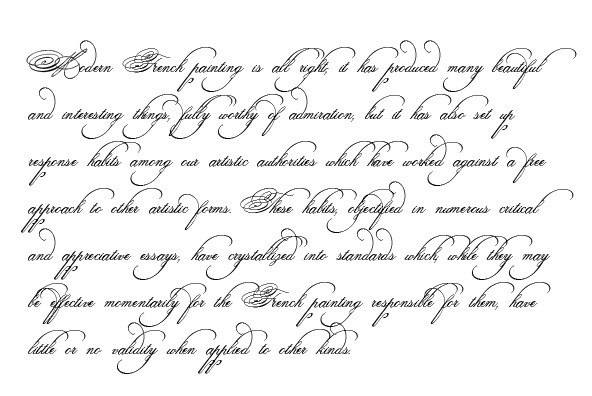
Каллиграфический почерк — как научиться писать красиво
В блогах, посвященных каллиграфии, уделяется много внимания способам создания красивых форм букв с помощью пера и чернил, но не так просто найти информацию по повседневному письму! В этом посте я раскрою восемь хитростей создания красивых рукописных записей любой ручкой на ваш вкус. А еще вы можете скачать прописи, чтобы отточить свой почерк!
Многие считают, что каллиграфия и есть красивый почерк, но это не так. Вообще, в каллиграфии буквы стилизованы и украшены – она ближе к искусству, нежели к простому письму. Письмо же, напротив, – совокупность знакомых приемов и стиль ежедневных заметок. В отличие от каллиграфии, в повседневном письме важнее скорость и удобство. А раз у каждого уникальный почерк, значит, возможности его совершенствования безграничны! Вот восемь хитростей, которые в этом помогут.
Пишите комфортной именно для вас ручкой
И тут уж каждому своё. Найти ту самую ручку, с которой вы сработаетесь, будет ой как непросто! Для себя я выбрала ручку Pilot G2 05 из-за широких штрихов, корпуса и приятного темно-черного цвета чернил.
Еще мне нравится то, как легко ей писать – не приходится напрягать руку, чтобы сделать четкий штрих.
Сейчас выбор ручек по-настоящему огромен, так что советую пробежаться по магазинам. Возьмите парочку тут, парочку там и опробуйте! И неважно, какие ручки вам больше по душе: гелевые, перьевые, авторучки… Та, с которой вы почувствуете связь, и будет идеальной.
Держите ручку свободно, без напряжения
Нежный, легкий захват – основа хорошего почерка. Легкий захват получается, когда мышцы руки не перенапряжены и ногти не начинают белеть от сильного нажима.
Многие сжимают ручку так крепко, что рука начинает побаливать уже в первые минуты письма. Зачастую мы делаем это непроизвольно, так что возьмите за правило каждые несколько минут мысленно проверять, свободно ли держите ручку.
Начните с разминки
Неважно, как вы собираетесь писать – курсивом или печатным шрифтом, вам будет сложно вывести аккуратные буквы без разогрева. Начните с пары завитушек и после такой разминки из-под вашей руки начнут выходить аккуратные и уверенные буквы.
Для этого упражнения отлично подойдет поле спиралек из прописей.
Или можно просто накрутить пару завитушек “от скуки” примерно такой формы.
Не бойтесь крутить листок
Нас с детства учили держать листок строго и ровно перед собой. Если вам так удобно – отлично! А если все-таки нет, смело крутите листок. Действительно многое зависит от того, под каким углом вы его положите!
Большинству правшей подходит обычное вертикальное положение листа… но не мне. Мне гораздо легче писать курсивом – моим основным стилем – когда лист повернут на 90 градусов. И это не шутка: а видео внизу тому подтверждение!
Удобное положение листа для каждого свое, так что смело пробуйте разные углы. Правшам советую сперва положить лист вертикально и поворачивать его влево до тех пор, пока писать не станет легко и удобно.
Левшам тоже предлагаю начать с вертикального положения, но поворачивать лист вправо.
Делайте упражнения в прописях
Курсив, представленный в прописях, не строго машинный. Я, напротив, делаю упор на тот стиль букв и слов, которым пользуюсь каждый день. Эти символы легки в написании и на письме плавно перетекают один в другой.
Практикуйтесь при любом удобном случае
Почерк, как почти все в жизни, нужно совершенствовать, постоянно применяя на практике. Чем больше полезных привычек и стилей, которые вам импонируют, вы используете на письме, тем лучше станет ваш почерк.
Упражняться можно по-разному: например, напишите кому-нибудь не имэйл или сообщение, а письмо от руки.
Если есть время и желание, начните вести дневник. Необязательно делать длинные записи – достаточно просто пары заметок о том, как прошел день!
Пишите на линованной бумаге или подкладывайте разлинованный лист
Красивые и ровные слова – кратчайший путь к аккуратному почерку! Когда пишите письмо, подкладывайте под белый лист листок из записной книжки. Он наверняка будет просвечивать, и вы сможете использовать линии листа как направляющие, чтобы все строки письма были ровными. А если вы не против разлинованных листов – пишите сразу на них.
В дополнение к этому пункту скажу: всегда используйте подложку. Неважно, какой лист вы выбрали для письма, под ним всегда должен быть еще один. Любая ручка почему-то начинает писать лучше на чуть более мягкой поверхности двух листов бумаги.
Выберите собственный стиль письма
Почерк изменчив, индивидуален и постоянно развивается. В отличие от каллиграфии, занимаясь которой вы всегда будете писать примерно одинаково, здесь у вас будут дни хорошего почерка и дни не самого удачного почерка (как в заметках ниже).
Во-первых, TenguGo вводит курсивные буквы в доступной форме, разбивая их на группы, такие как «Старые друзья», в которых буквы похожи на английские буквы, и «Ложные друзья», где буквы могут выглядеть одинаково на английском и Русские, но не совсем то же самое. После печатных букв, транслитерации, того, как буквы звучат, и звукового произношения, вы увидите прописные и строчные буквы каждой буквы. Вы также можете прокрутить до конца каждой страницы примеры слов, в которых используются эти буквы, а также звуковое произношение, что дает вам простой способ соединить печатные слова, курсивные слова, произносимые слова и англоязычное значение.